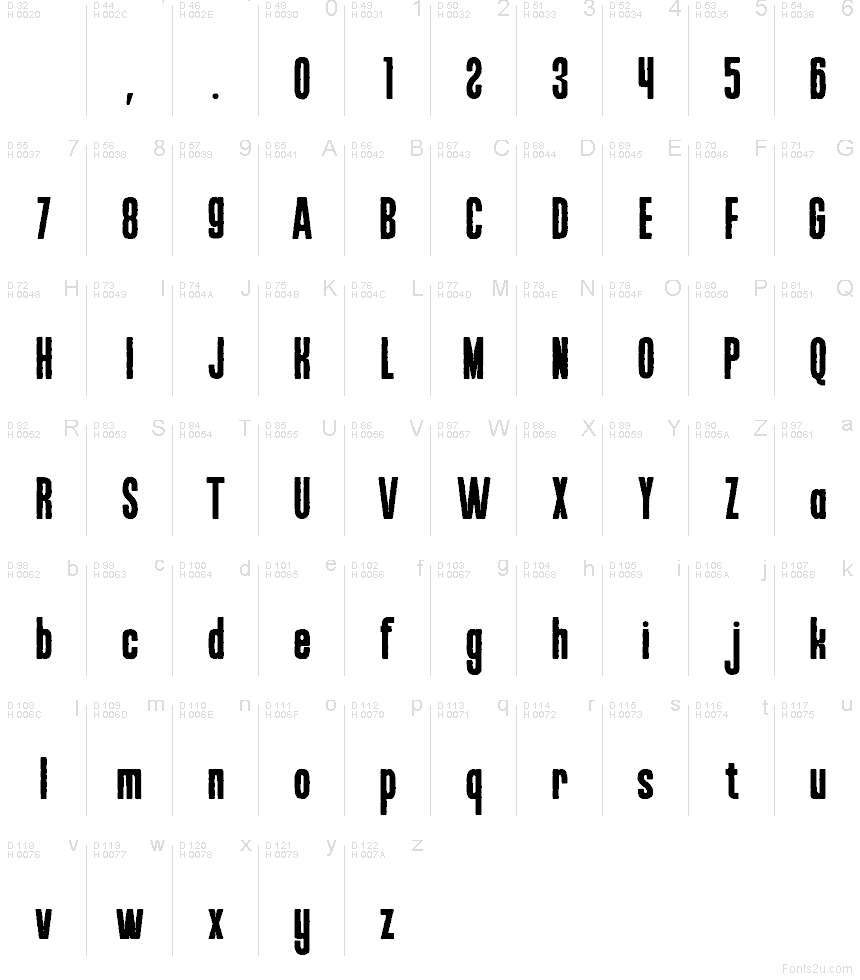
Retroforge Condensed
Retroforge Condensed od Retroforge (Muksal Creative) je bezplatné erodované display písmo, které vyniká svými vysokými, úzkými písmeny a hlubokými opotřebovanými zářezy, které procházejí tahy jako seškrábaný inkoust. Efekt poškození působí strukturálně, nikoliv jako pouhá povrchová vrstva, což fontu dodává hrubou tiskovou texturu při zachování kompaktní a vzpřímené siluety.
Tato kombinace skvěle funguje u plakátů, obalů alb, brandingu barů, herní grafiky a obalů, kde úzké provedení umožňuje těsné sázení bez ztráty drsného povrchu. Nejlépe vynikne u krátkých nadpisů a log, zejména pokud hledáte vzhled zvětralého nápisu namísto obyčejného zúženého display stylu.